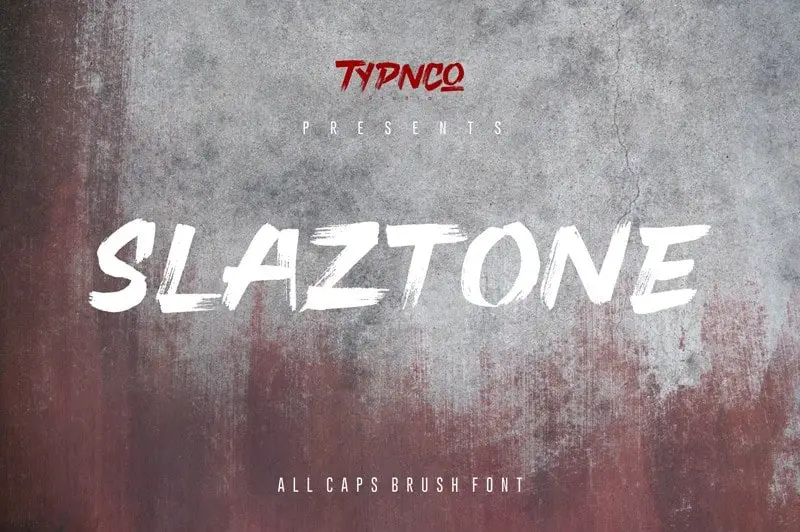
Slaztone Brush Font
Slaztone Brush Font é uma tipografia script feita a mão no papel com um canetão secante. Este tipo de letra traz aos seus projetos um estilo casual e autêntico, perfeito para design de roupas, camisetas, promoções ou até mesmo para ilustrações halloween. É um tipo em letras maiúsculas que incorpora traços agressivos da mão do artista e uma posição itálica característica. Adicionalmente, inclui pontos suspensivos, números, símbolos e a versão internacional dos caracteres, tornando-o perfeito para qualquer aplicação que exija um toque de escrita manual. Este font é ideal para projetos como identidade visual, logomarcas, embalagens, materiais promocionais, cartazes, camisas personalizadas ou mesmo a criação de t-shirts temáticas de Halloween. Slaztone Brush Font é uma excelente adição ao seu arsenal de tipos digitais.